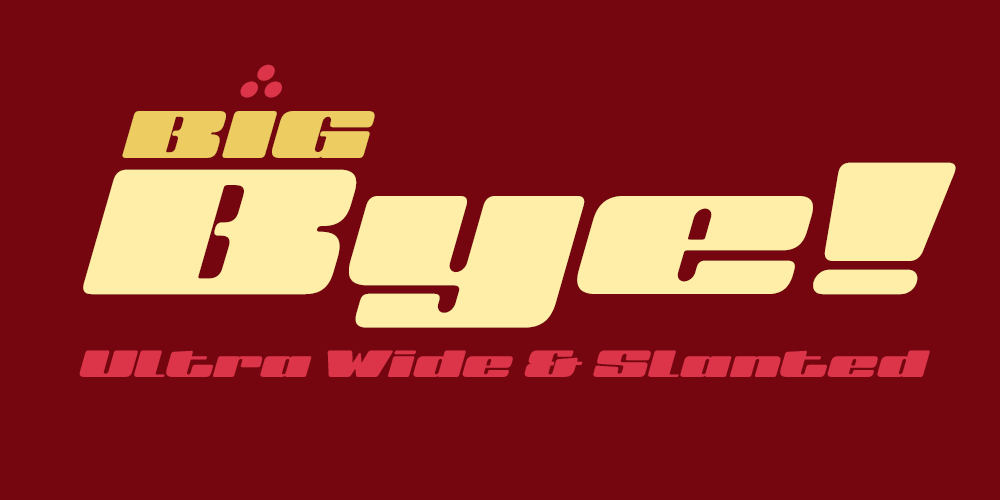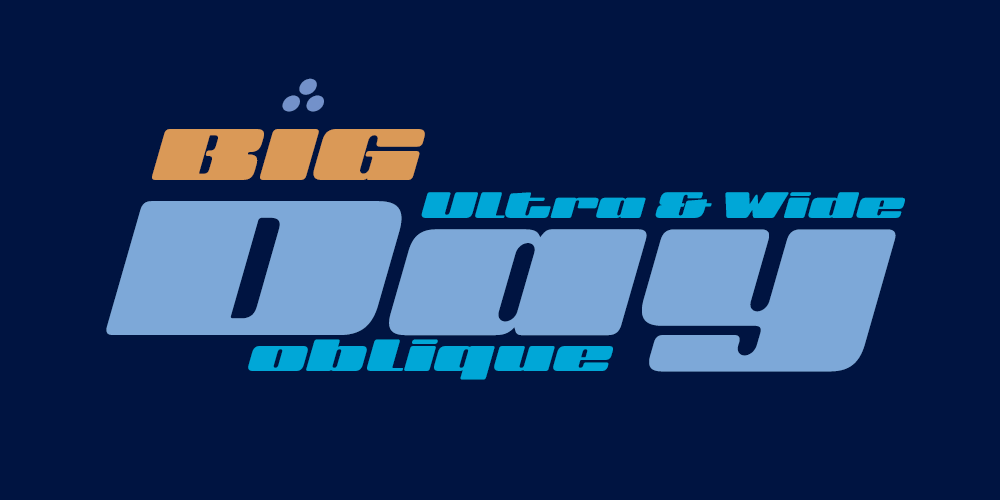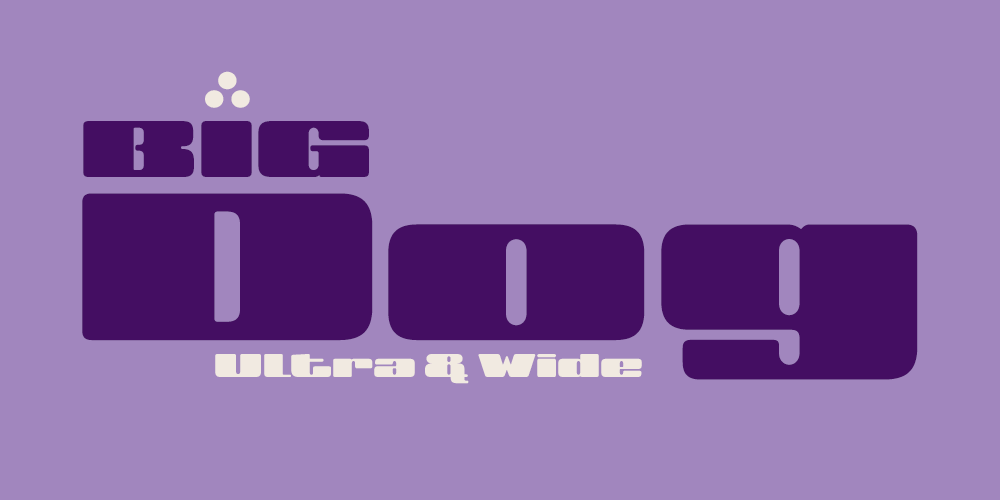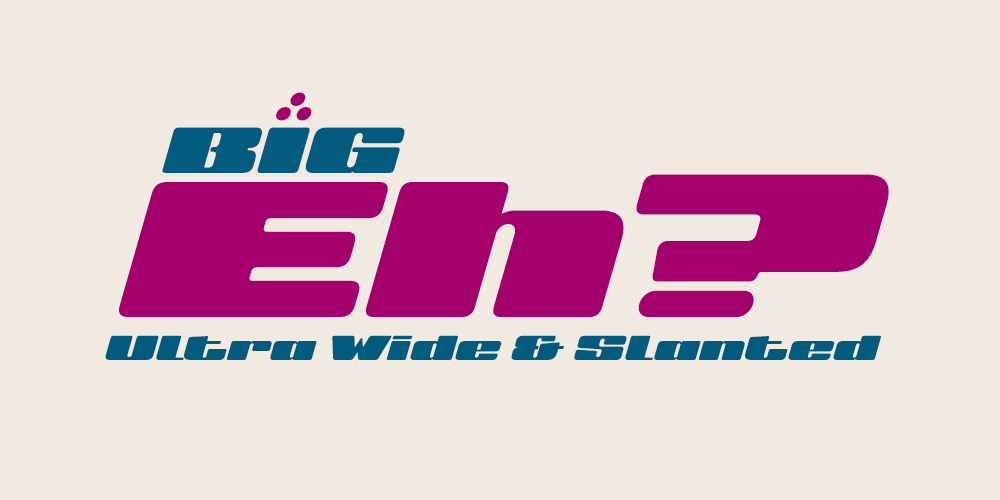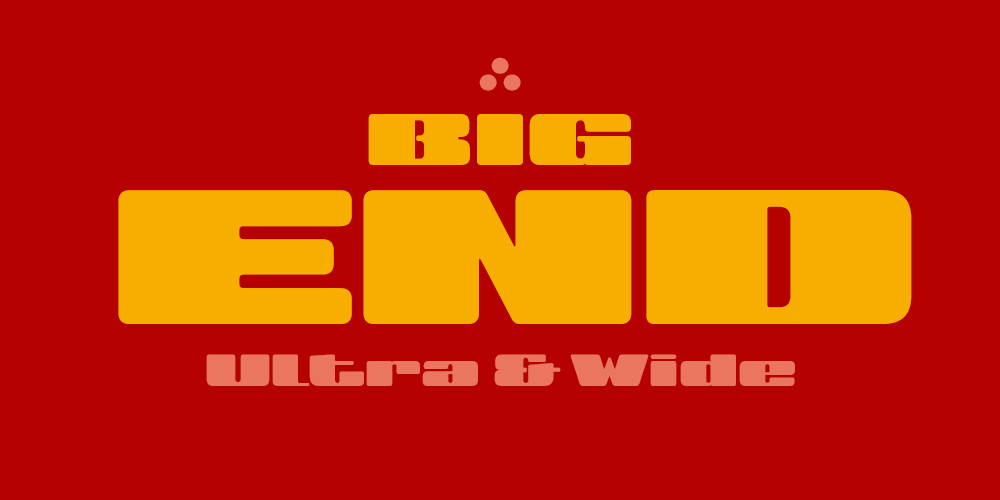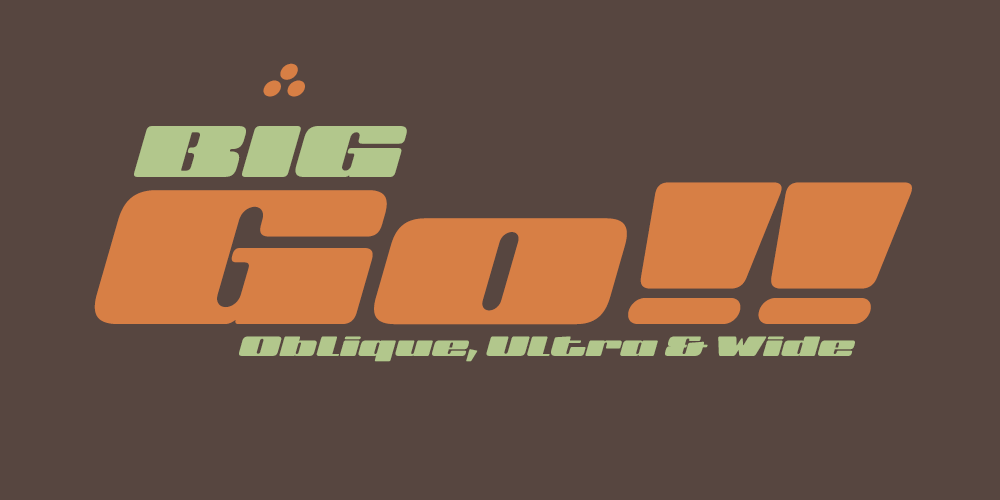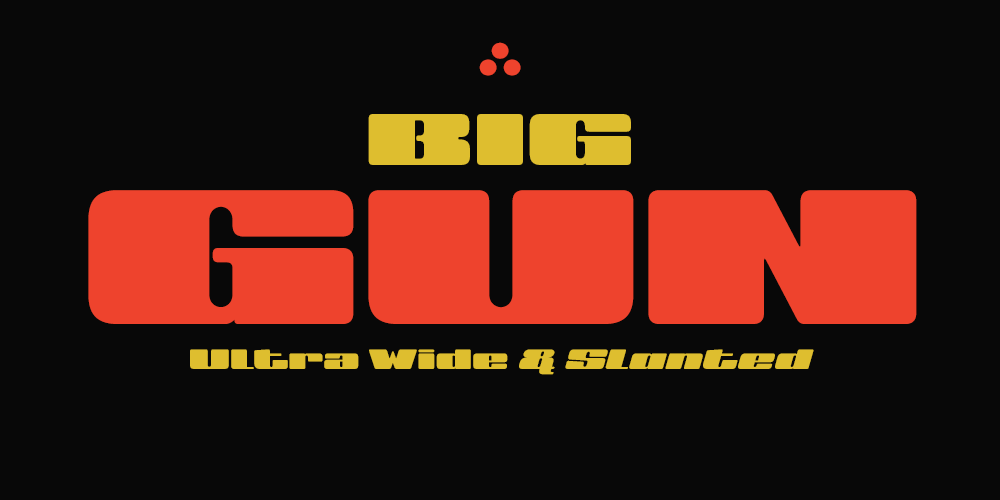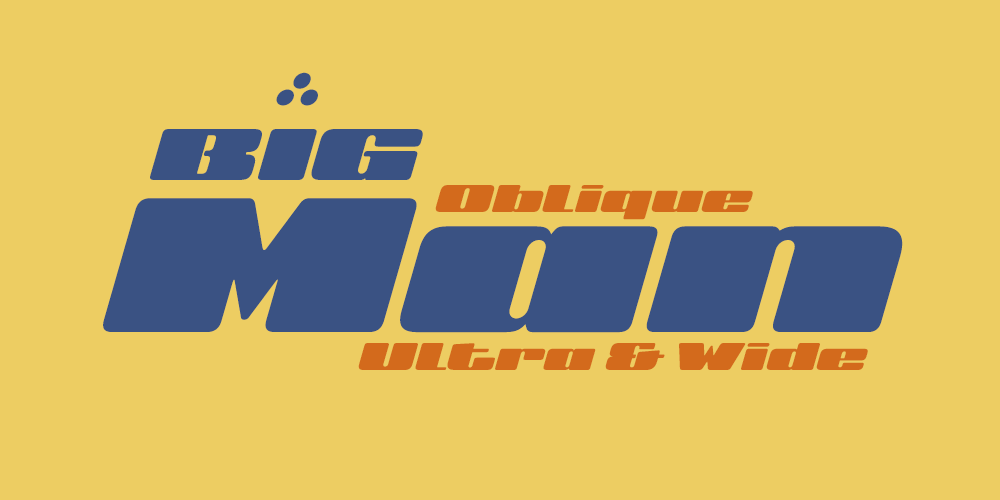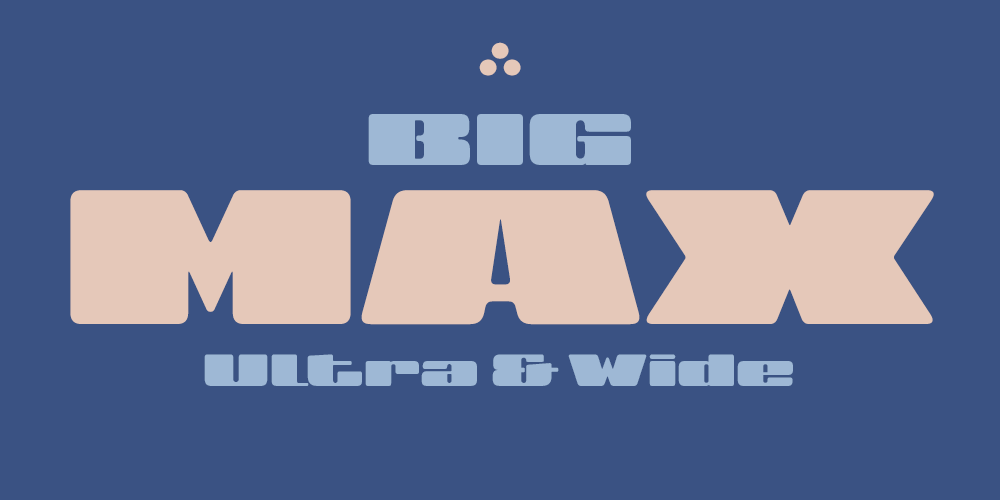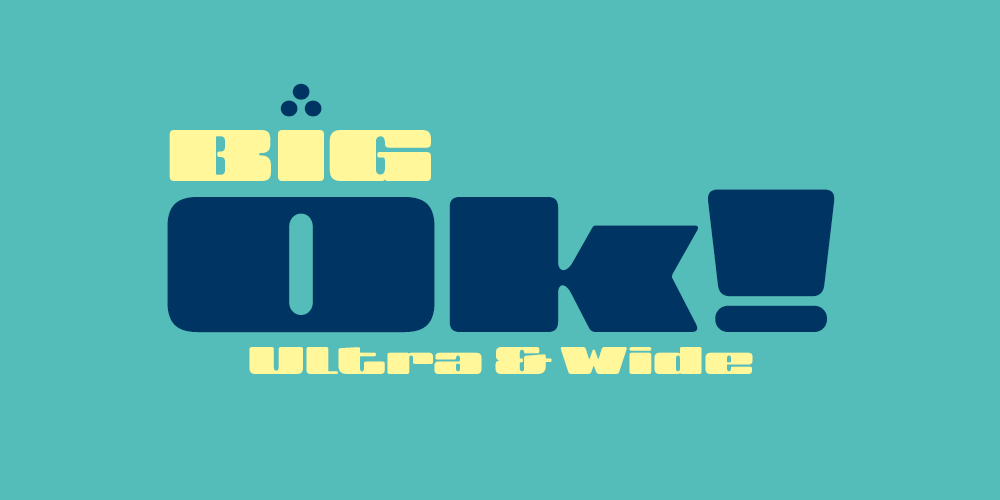
BIG: Roman & Oblique!
Estilo: Sans Serif, Display, Chunky, Thickset, Black
Proporción: Ultra wide, Extra expanded
Alternates: 146
Dos versiones, doble actitud:
- BIG Ultra Wide (Roman): Firme, poderosa, innegable.
- BIG Ultra Wide Slanted: Con una inclinación decidida de 16° que aporta velocidad, contemporaneidad y un aspecto inconfundible.
He reducido al mínimo los ascendentes y descendentes, son cortos, casi anecdóticos, porque aquí lo que importa es la presencia horizontal, me centré en cada detalle para realzar esa anchura que la hace única. El resultado es una textura visual poderosa, coherente y perfectamente legible, gracias también a una precisa definición de métricas y kerning, así como a un cuidado trabajo de corrección óptica en cada forma, donde he realizado innumerables correcciones ópticas en ambas versiones para que cada palabra, cada línea, sea tan equilibrada como impactante.
Y para rematar esa personalidad imponente, todas las esquinas y ángulos tienen un acabado redondeado, dándole un toque moderno y amable, en contraste a su fuerza bruta.
Sí, BIG se ve bien… pero sobre todo se lee bien.
He desarrollado esta tipografía pensando en la escritura de palabras de tres letras. Palabras cortas, potentes, que dejen huella. BIG convierte cada trigrama en una declaración visual. Piensa en palabras como ART, DAY, MAX, BYE, YES, WOW, HUG… y verás cómo toman vida.
Además en su interior, BIG alberga un sólido set de funciones avanzadas OpenType (¡Las posibilidades son infinitas!):
- Letras y números alternativos.
- Fracciones dinámicas.
- Signos matemáticos.
- Flechas.
- Y compatibilidad con múltiples idiomas gracias al set de caracteres Latin Extended-A.
BIG es la elección perfecta cuando necesitas que tu mensaje resuene.
Es ideal para:
- Grandes títulos que exigen atención.
- Folletos y pósters que necesitan comunicar con fuerza.
- Cartelería que no pasa desapercibida.
- Logotipos e imagen corporativa identidades robustas y memorables.
- Embalaje de productos que necesitan destacar en el estante.
- Señalización que guíe con autoridad.